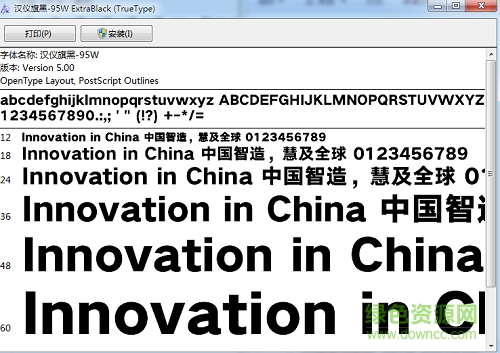
hyqihei iew字體又稱漢儀旗黑95w字體,是一款非常醒目的中文字體,字形筆畫粗獷有力,筆畫細(xì)節(jié)上的修飾既增強(qiáng)了字體的設(shè)計(jì)感,有喜歡的朋友歡迎來綠色資源網(wǎng)下載使用!
hyqihei iew字體是一款極具個性的黑體字體,字體非常端莊大方,可以廣泛應(yīng)用于廣告設(shè)計(jì)、宣傳海報(bào)、ppt、影視制作以及任何使用文字的領(lǐng)域!